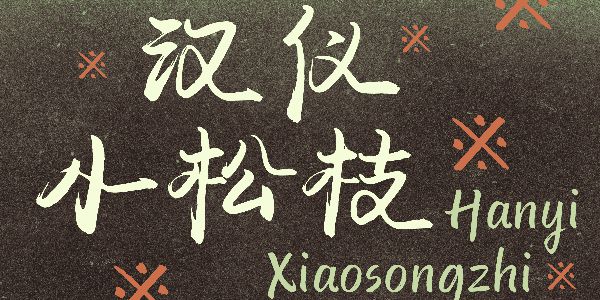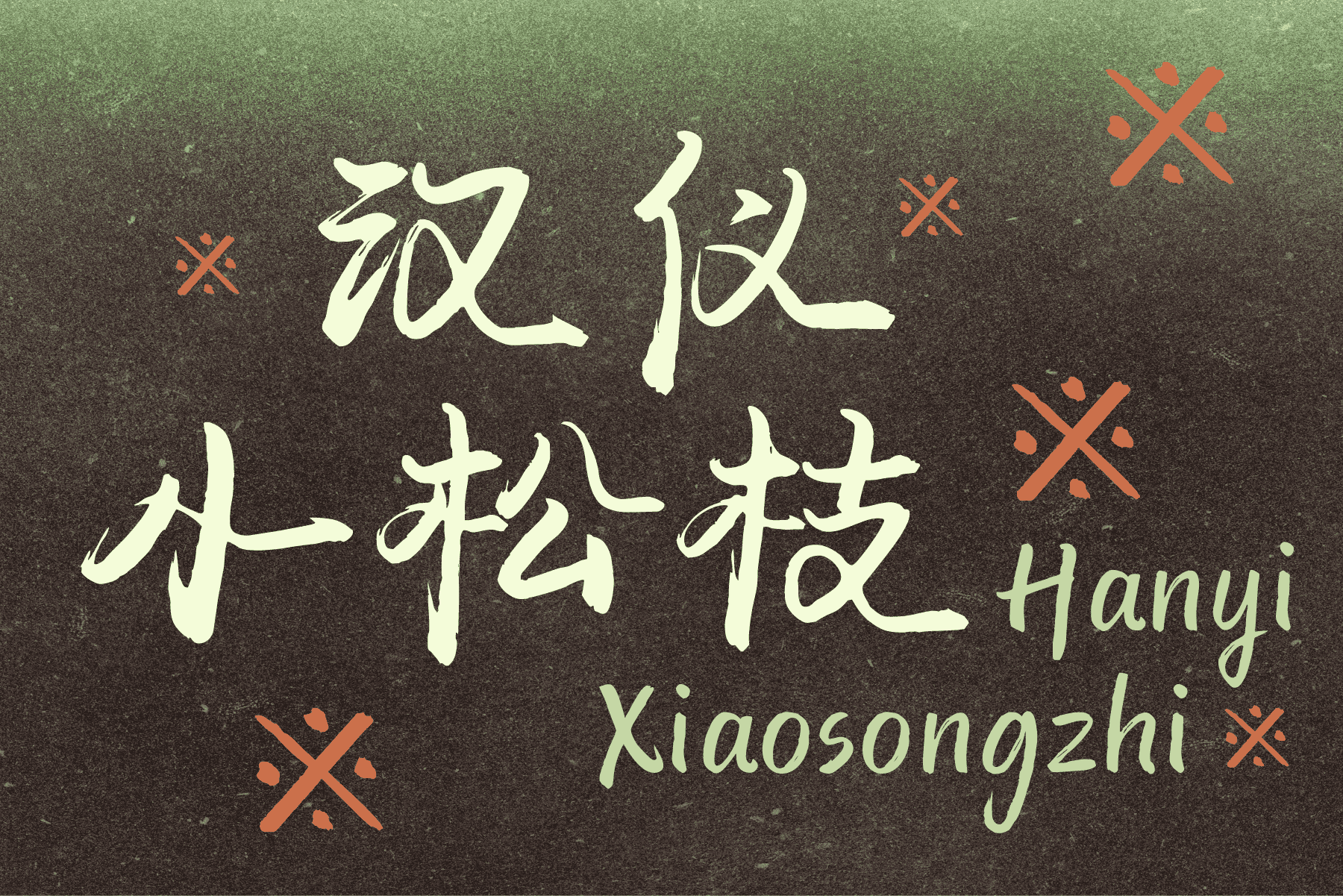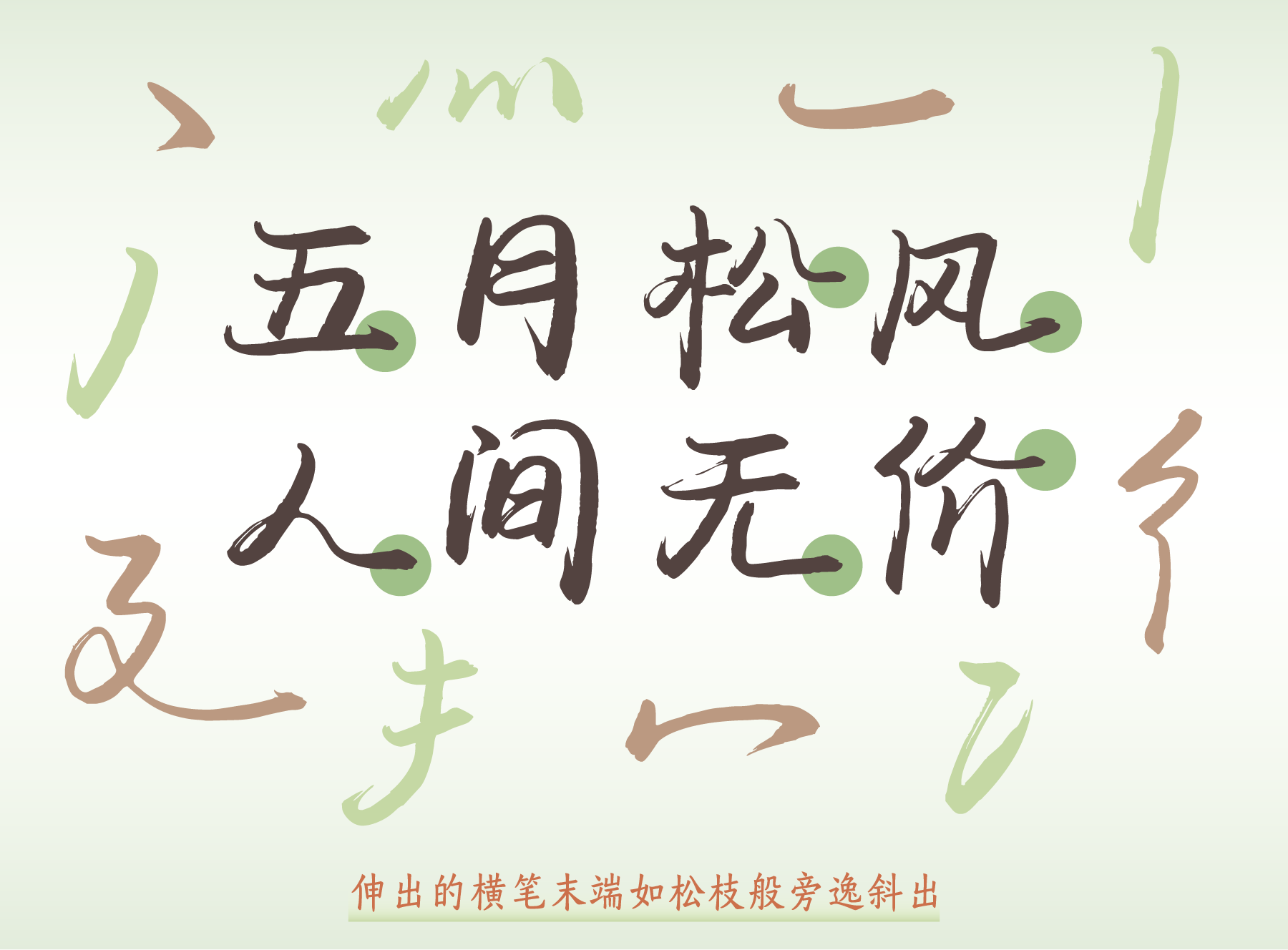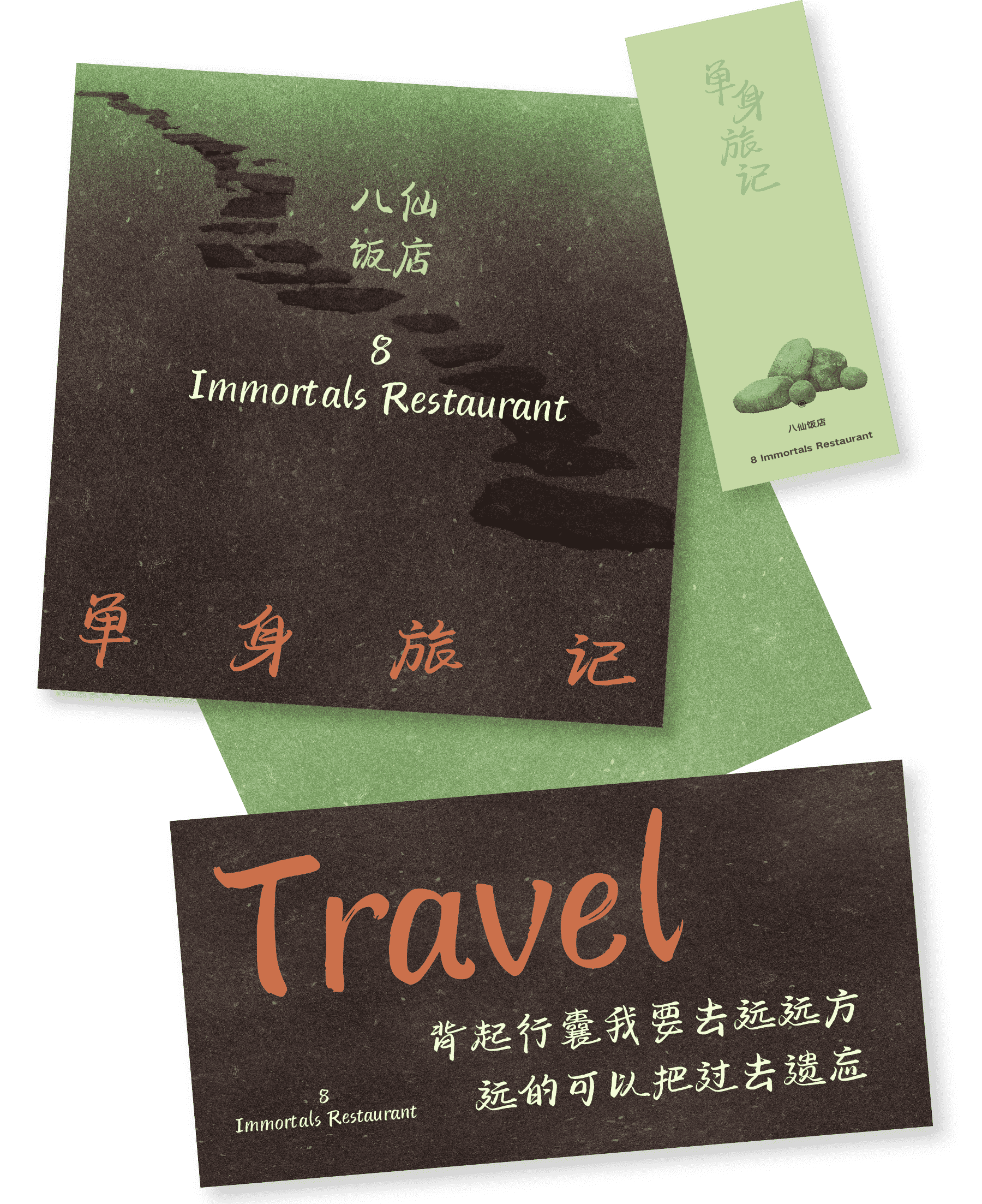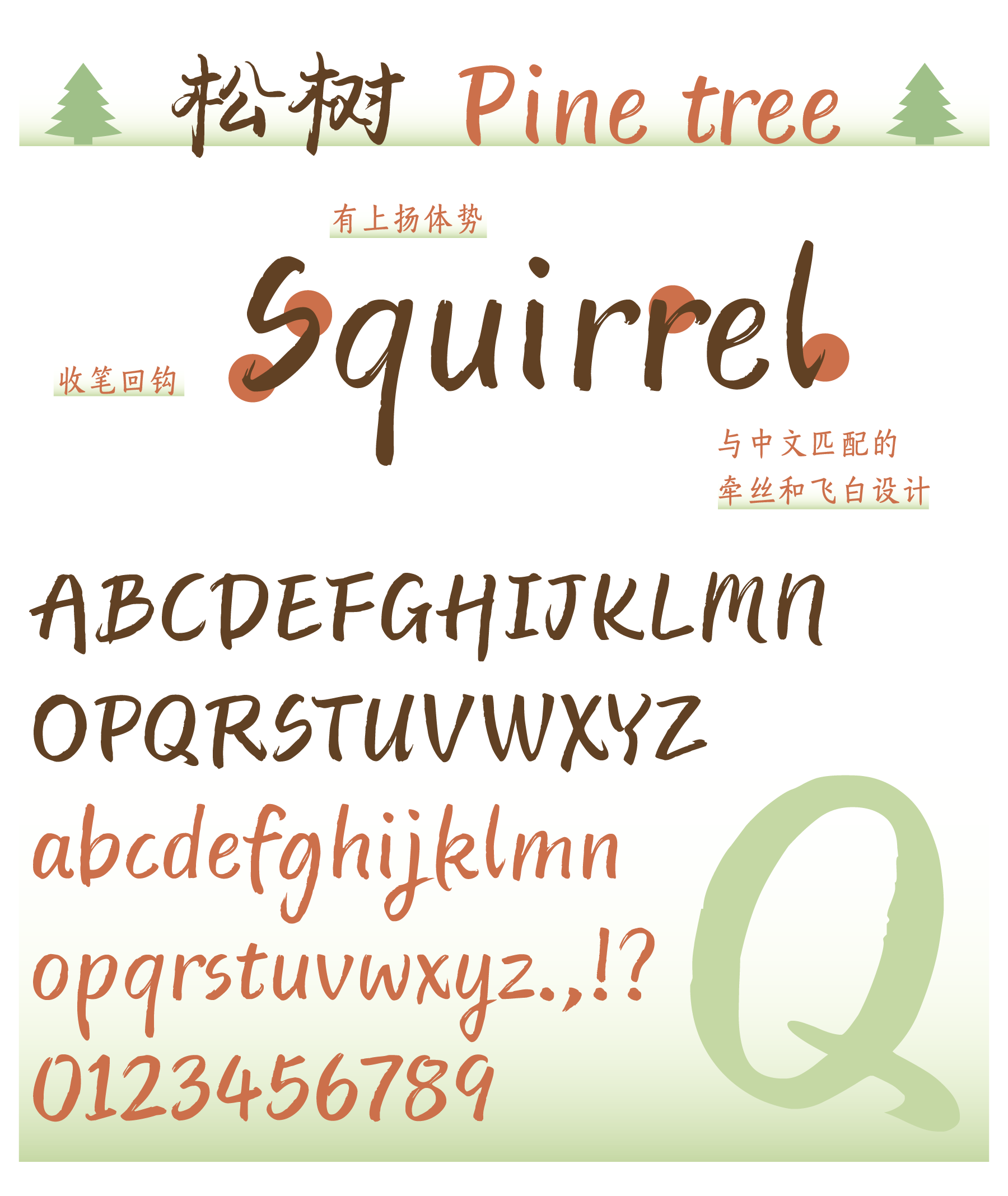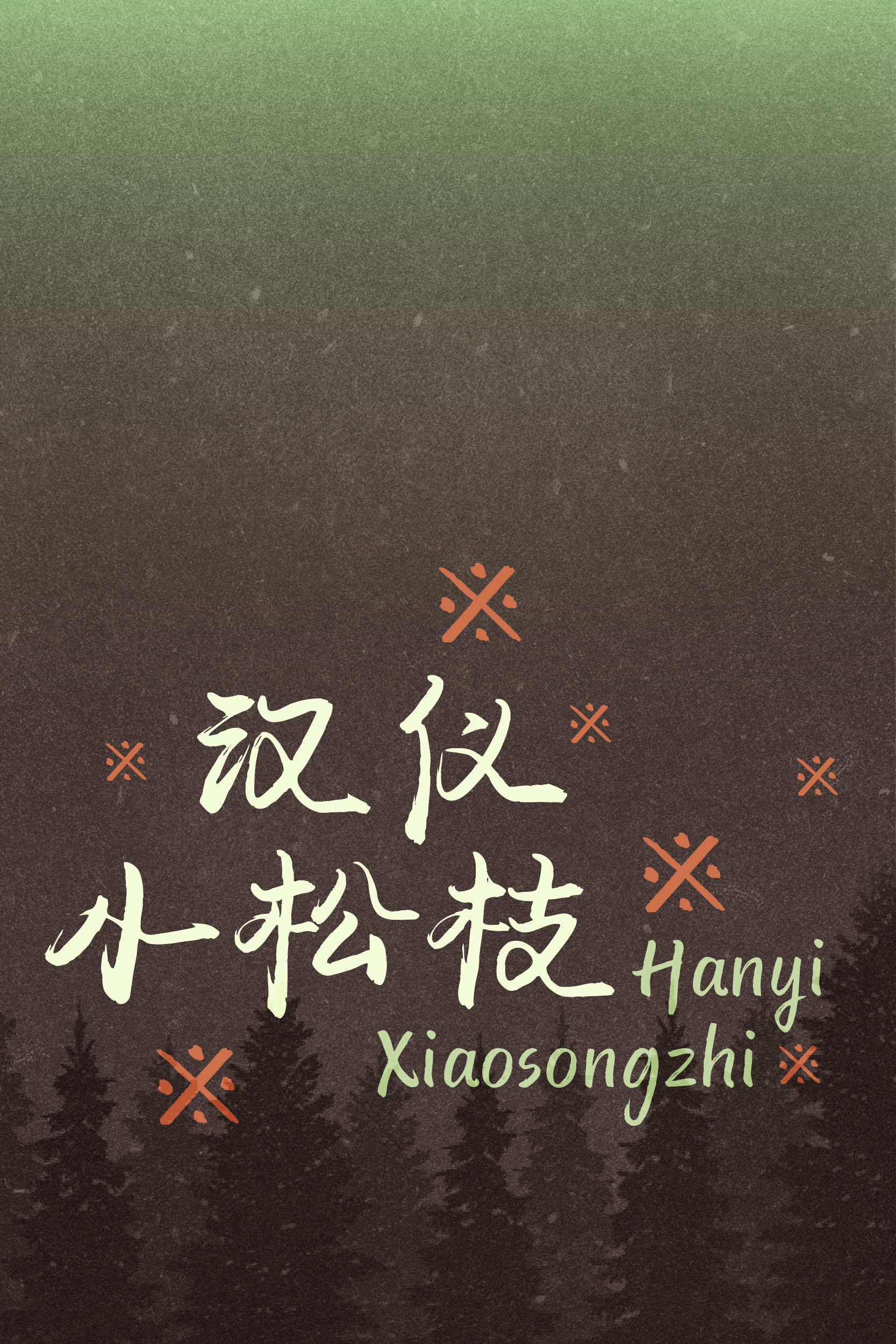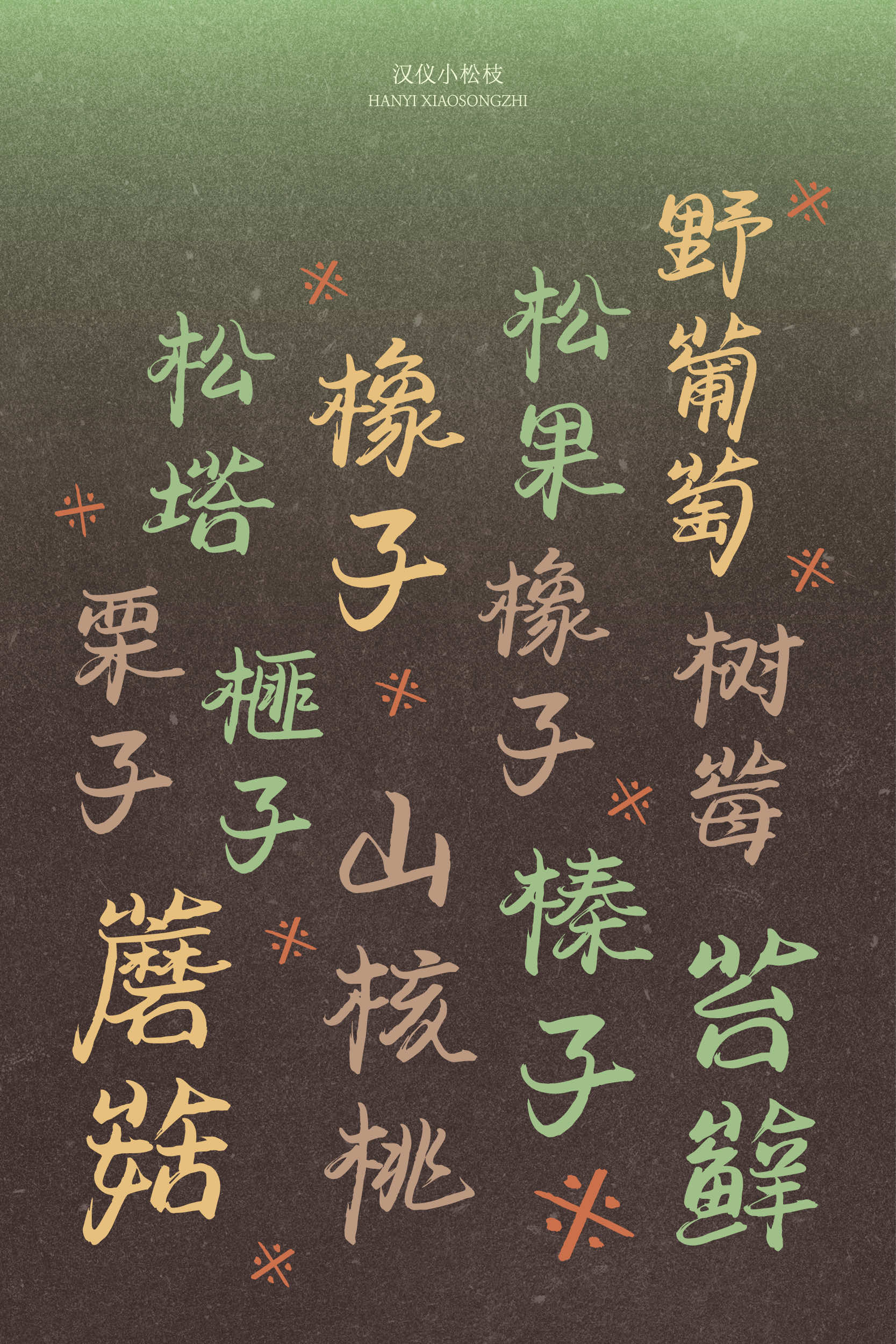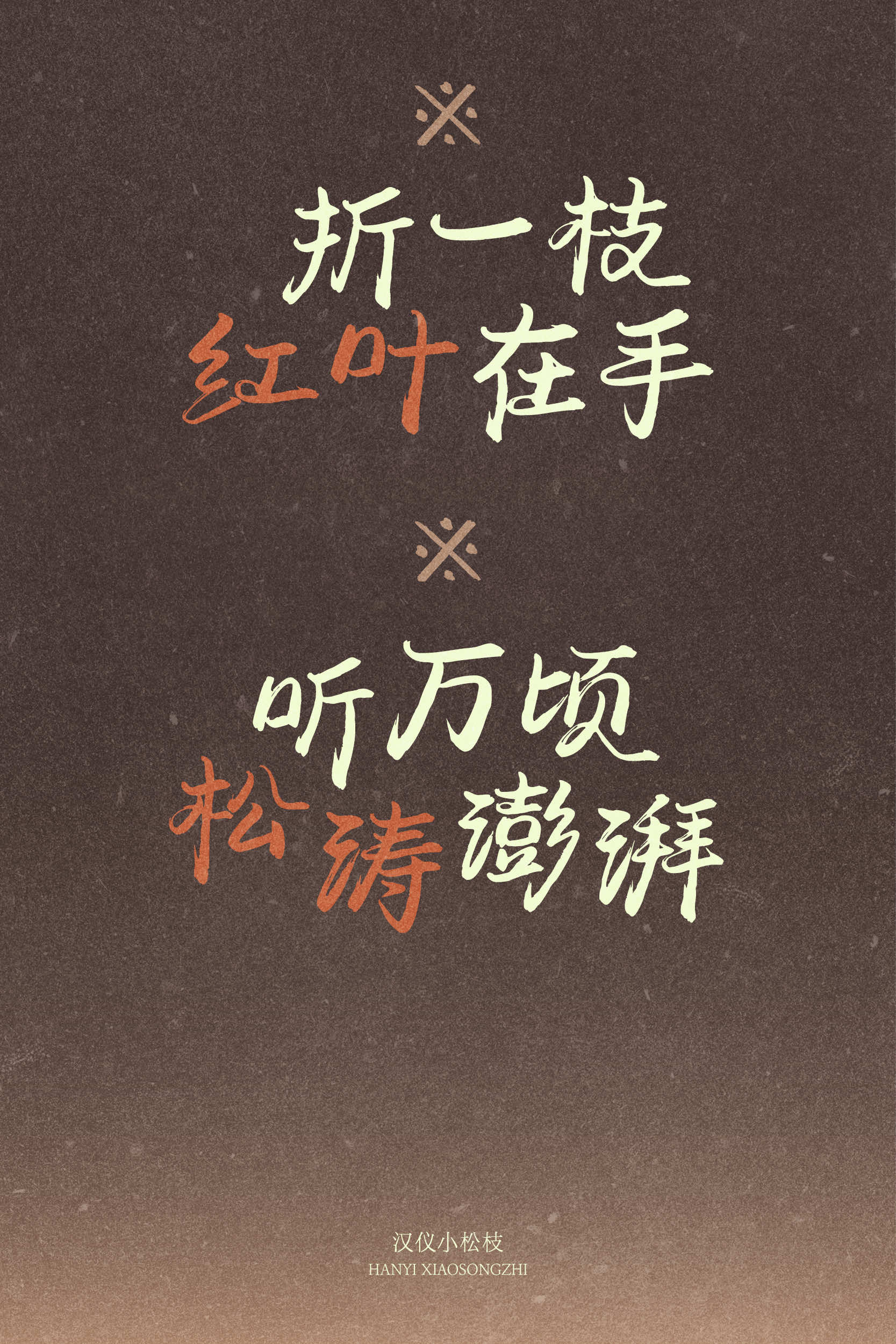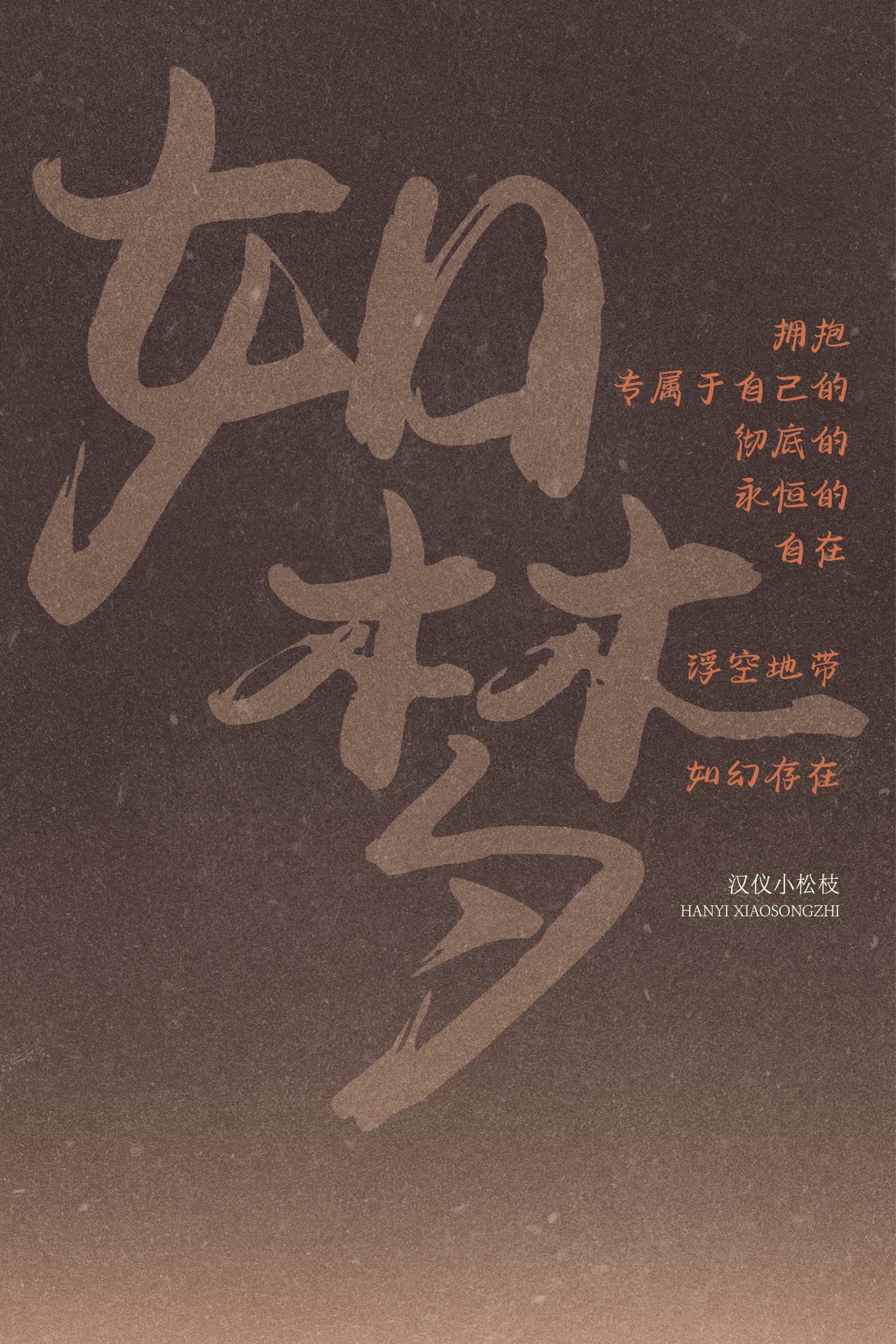
用松枝搭出一款字体
汉仪小松枝,是由汉仪字库签约作者孙小松创作的一款清新自然的手写字体。以松弛的笔法书写,字形左右舒展,有微倾斜感;强调每个字结尾的一笔,如松枝般旁逸斜出,线条柔韧,流畅自然,笔画之间有轻微的牵丝和飞白,整体风格清新明快,舒缓而治愈。这款字体可用于专辑唱片、书籍绘本、影视综艺、广告海报等使用场景,适合自然休闲主题,以其轻松的书写传达返璞归真、无忧无虑的视觉语言。
以松弛的笔法书写,中宫略收而笔画舒展,有微倾斜感,整体气质轻松自在,略带扬势。
笔画强调每个字结尾的最后一笔,如松枝般旁逸斜出,线条柔韧,书写流畅自然,笔画之间有轻微的牵丝和飞白。
这款字体松弛的手写感舒缓而治愈,可用于专辑唱片、书籍绘本、影视综艺、广告海报等使用场景,适合自然休闲主题,以其轻松的书写传达返璞归真、无忧无虑的视觉语言。
汉仪小松枝的西文部分选择了手写涂鸦的风格,轻松自在,与中文有着相同的书写流畅度。